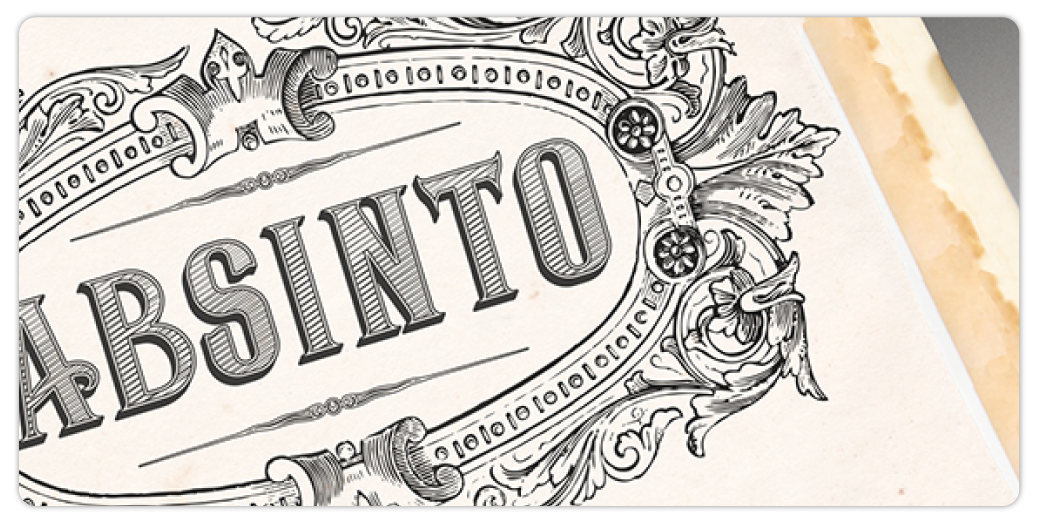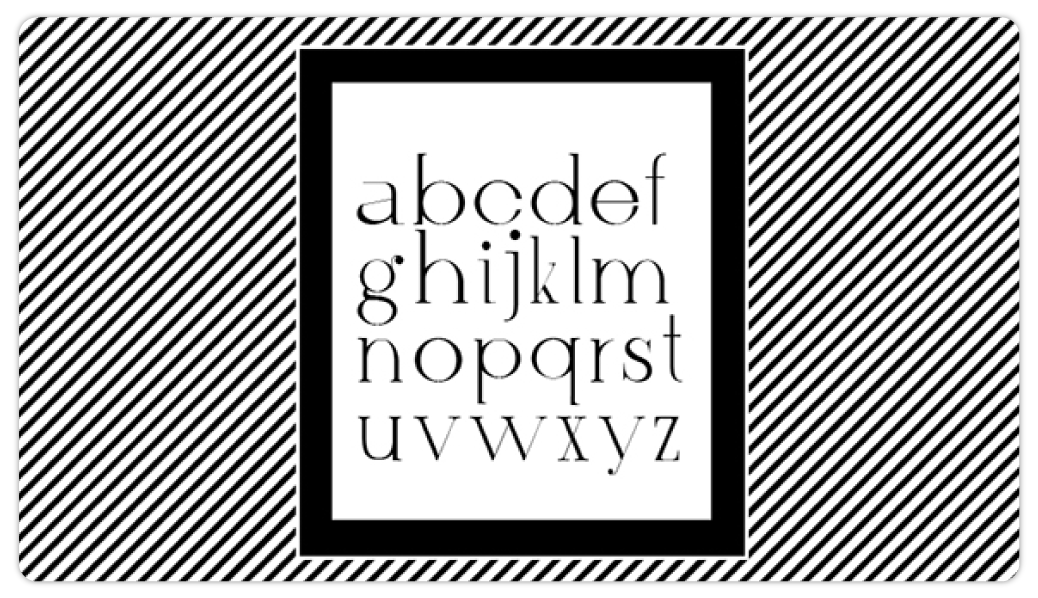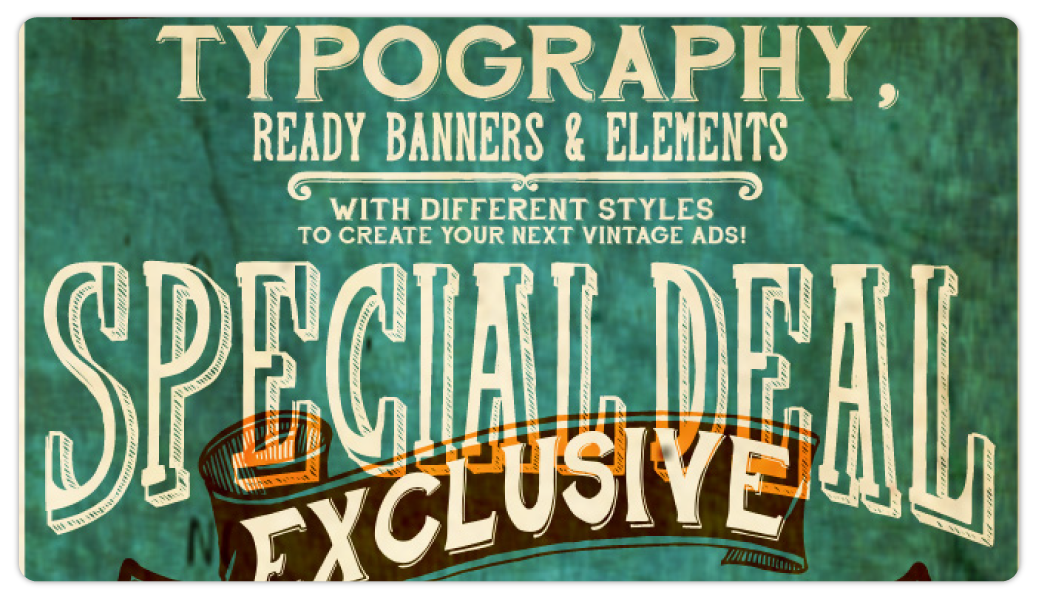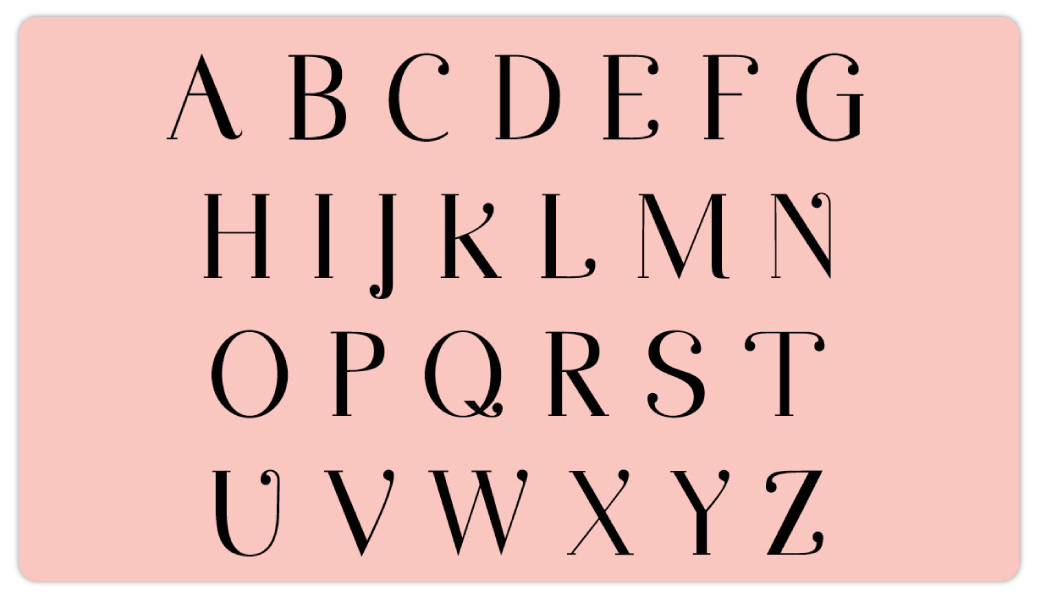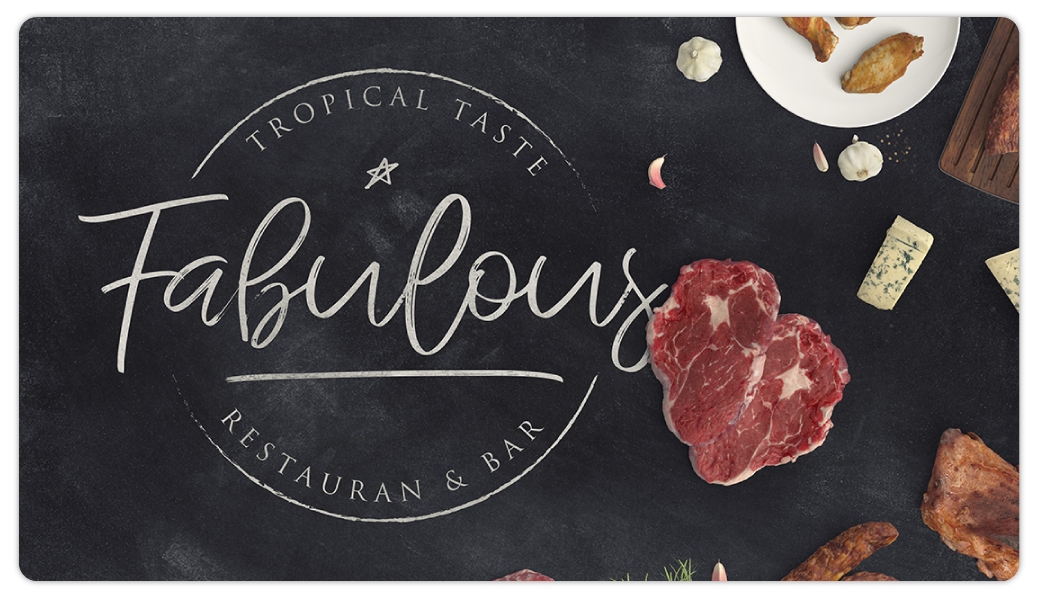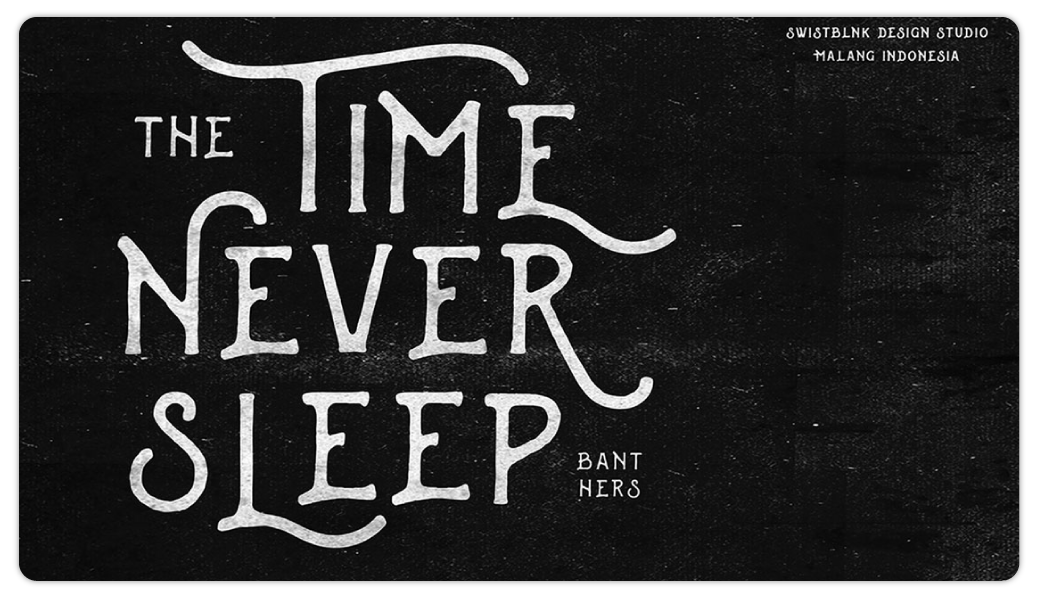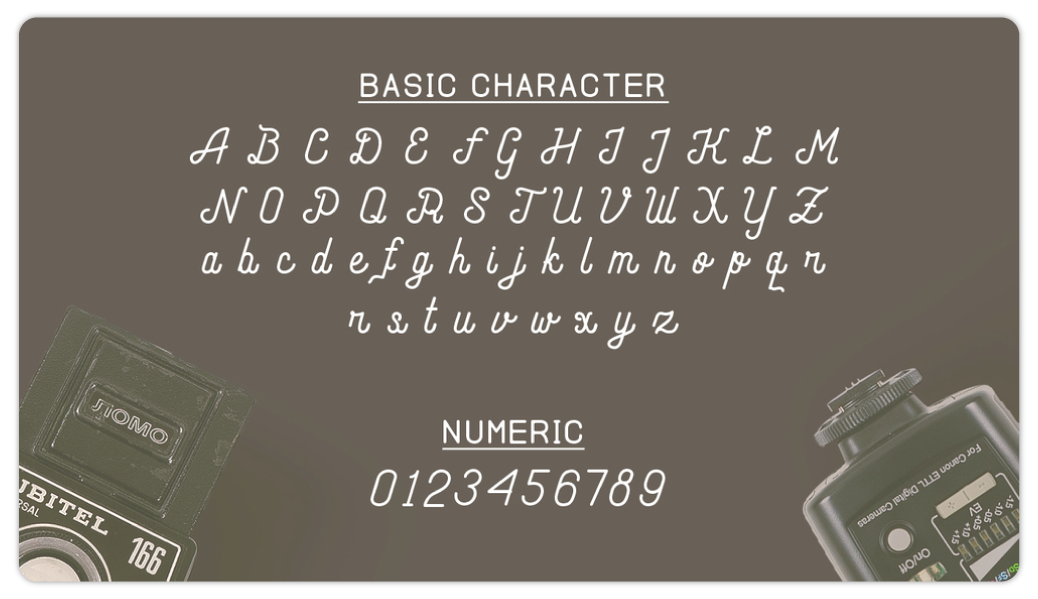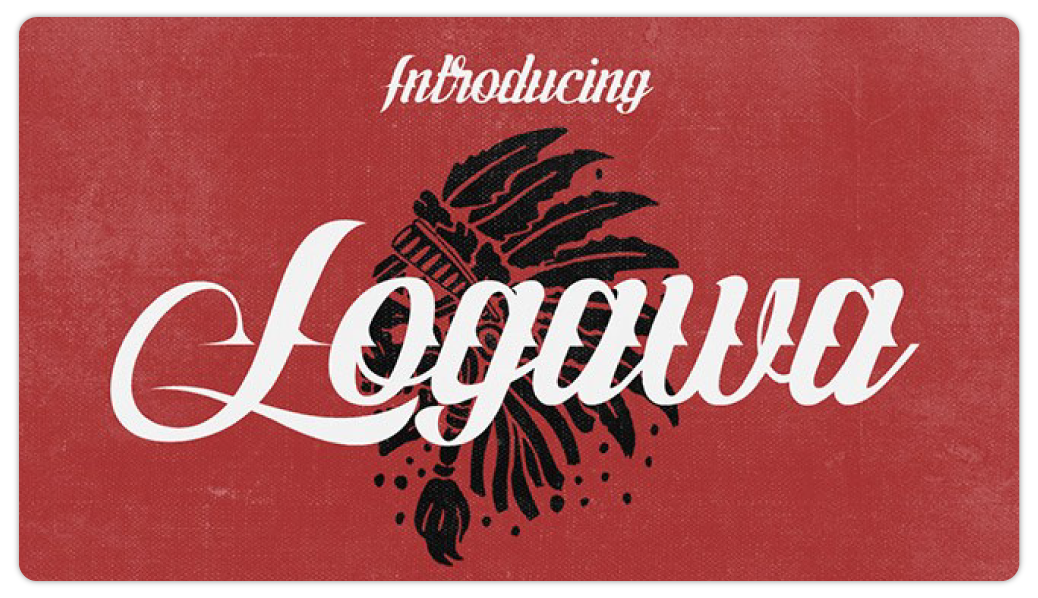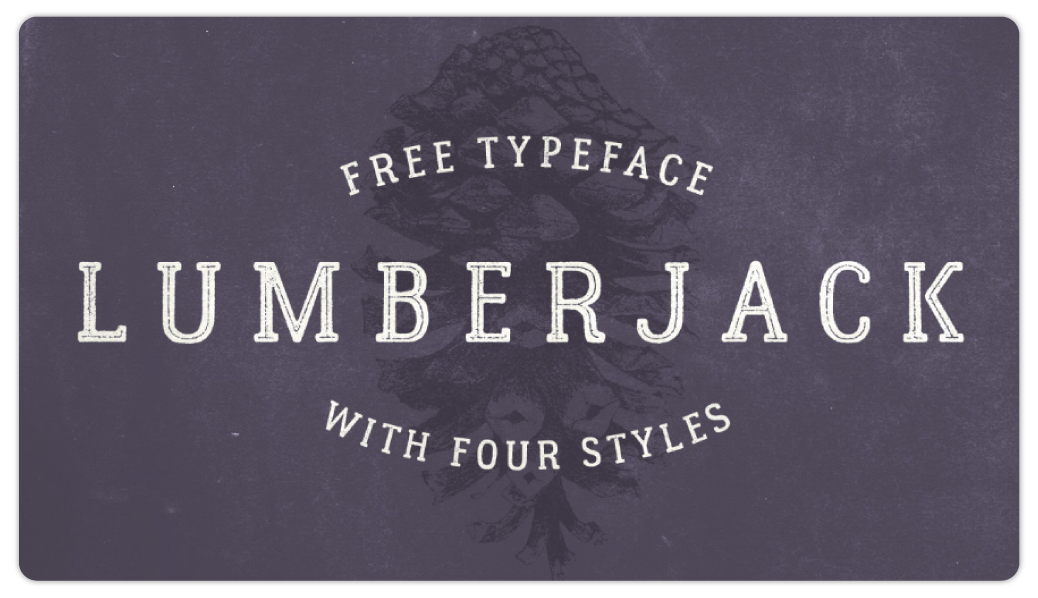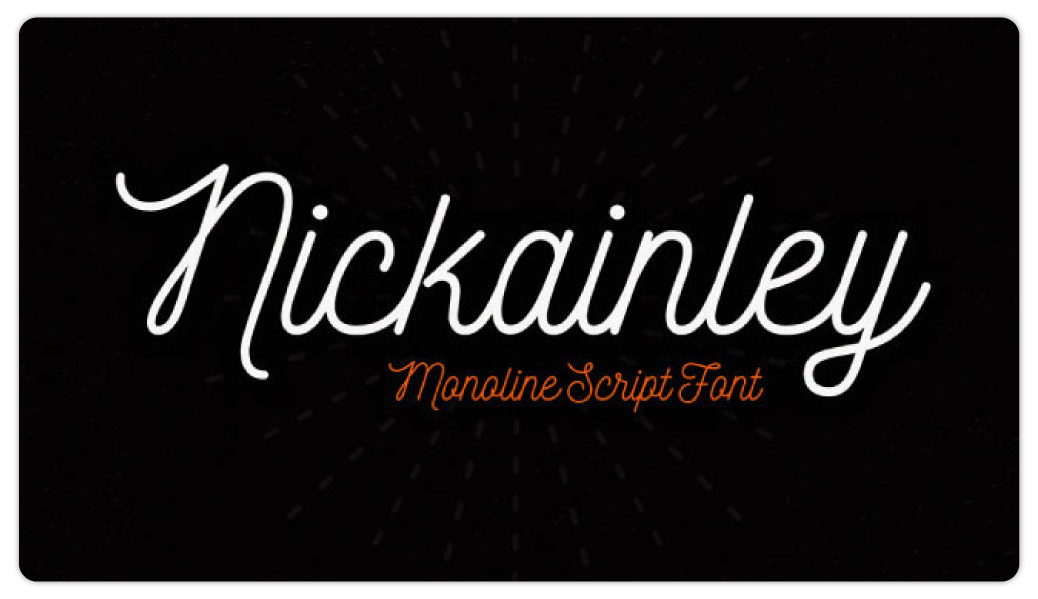
45 tipografías vintage gratis para tus diseños
Aun con toda la tecnología moderna de la que se puede valer un diseñador, muchos de ellos siguen romantizando el pasado y optando por utilizar tipografías vintage a la hora de trabajar.
Sin duda, la xilografía –una antigua técnica de impresión con plancha—y los letreros hechos y pintados a mano continúan proyectando de una manera particular distintos aspectos a la hora de diseñar, a pesar de que los avances son muy significativos.
Esta pasión por lo antiguo o lo pasado ha tomado fuerza en los últimos años, haciendo que muchos diseñadores opten por tipografías vintage o retro. Por eso, te presentamos un listado con 45.
¿Por qué usar tipografías vintage?
Las tipografías vintage son muy útiles porque le dan gran personalidad a cualquier forma de comunicación digital que deseemos diseñar.
Por lo anterior, es común ver marcas, páginas web y aplicaciones que se valen de estos estilos para llamar la atención de la gente.
En la web es muy fácil encontrar diferentes tipografías vintage, pero entre tanto contenido podemos toparnos con múltiples fuentes que no son de gran calidad. De ahí la importancia de saber dónde buscar y dedicarle cierto tiempo a esta tarea.
Sin importar si eres un diseñador profesional o si eres sólo una persona amante de este tipo de fuentes, estamos seguros de que estas 45 tipografías vintage te agradarán y funcionarán perfecto para sea lo que sea que realices.
Mejores tipografías vintage gratuitas
1. Rudelsbergtipografia-vintage-02
Esta tipografía vintage fue diseñada por Dieter Steffmann e incluye mayúsculas, minúsculas y números, además de que te permite colocar acentos y demás caracteres especiales, por lo que tus diseños tendrán una excelente calidad.
2. Canter
Canter admite únicamente letras en mayúscula, pero permite marcar una diferencia entre mayúsculas y minúsculas gracias al tamaño de la letra (la minúscula es más pequeña).
Esta fuente estilo vintage fue creada por Christopher J. Lee, un diseñador de Nueva York, Estados Unidos, y sin duda le dará un toque muy particular a cualquiera de tus diseños.
Esta tipografía vintage es mayormente utilizada en titulares y carteles.
3. Lazer 84
tipografia-vintage-04
Esta tipografía vintage fue diseñada por Sunrise Digital, está inspirada en los años 80 e incluye números, símbolos y acentos.
Únicamente admite caracteres en mayúsculas.
4. Streetwear
Streetwear es una tipografía vintage con gran estilo, que resulta ideal para diseñar logos, posters o camisetas.
Contiene elementos que hacen que relaciones esta fuente con la moda y el deporte de los años 70, dándole un toque diferente y divertido a tus diseños.
También podrás experimentar con sus caracteres alternativos a través del Opentype de Adobe Illustrator o de InDesign.
5. Bernier
Esta fuente de aspecto vintage fue diseñada por Ryan Pyae, incluye todas las letras en mayúscula y viene con tres estilos diferentes: regular, sombreado y desgastado.
Es utilizada generalmente para diseñar posters o logotipos y puedes descargarla aquí.
6. Lobster
Es una tipografía vintage condensada en negrita que incluye cientos de ataduras alternadas y sutiles. Es conocida como la nueva Comic Sans, debido a que es la favorita de muchos diseñadores.
Fue diseñada por Impallari Type y estamos seguros de que te encantará y de que les dará un toque diferente a todos tus diseños. Descarga aquí.
7. Pacífico
Esta fuente tipográfica fue creada por el diseñador Vernon Adams y es una divertida fuente de escritura manuscrita que está inspirada en la cultura surf americana de los años 50.
Incluye mayúsculas, minúsculas, números y caracteres especiales y puedes descargarla aquí.
8. Arkana
Arkana es una tipografía vintage muy elegante que viene en dos estilos: vintage y rugoso, lo que les dará a tus creaciones un aspecto auténtico.
Es ideal a la hora de diseñar carteles o logotipos. Descarga aquí.
9. Rispa
Esta fuente vintage fue diseñada por Konrad Bednarski, quien se inspiró en París, su ciudad natal.
Viene en tres estilos: light, regular y bold. Descarga aquí.
10. Leathery
Esta tipografía vintage está inspirada en la Belle Époque europea, antes de la Primera Guerra Mundial y es ideal para logos o carteles.
11. Spicy rice
Spicy rice nos transporta a los años 60, cuando tenía presencia el gran movimiento hippie.
Los carteles con esta tipografía vintage nos recuerdan aquellos momentos en los que la gente se subía a una antigua Volkswagen y ponía música psicodélica a todo volumen mientras viajaba.